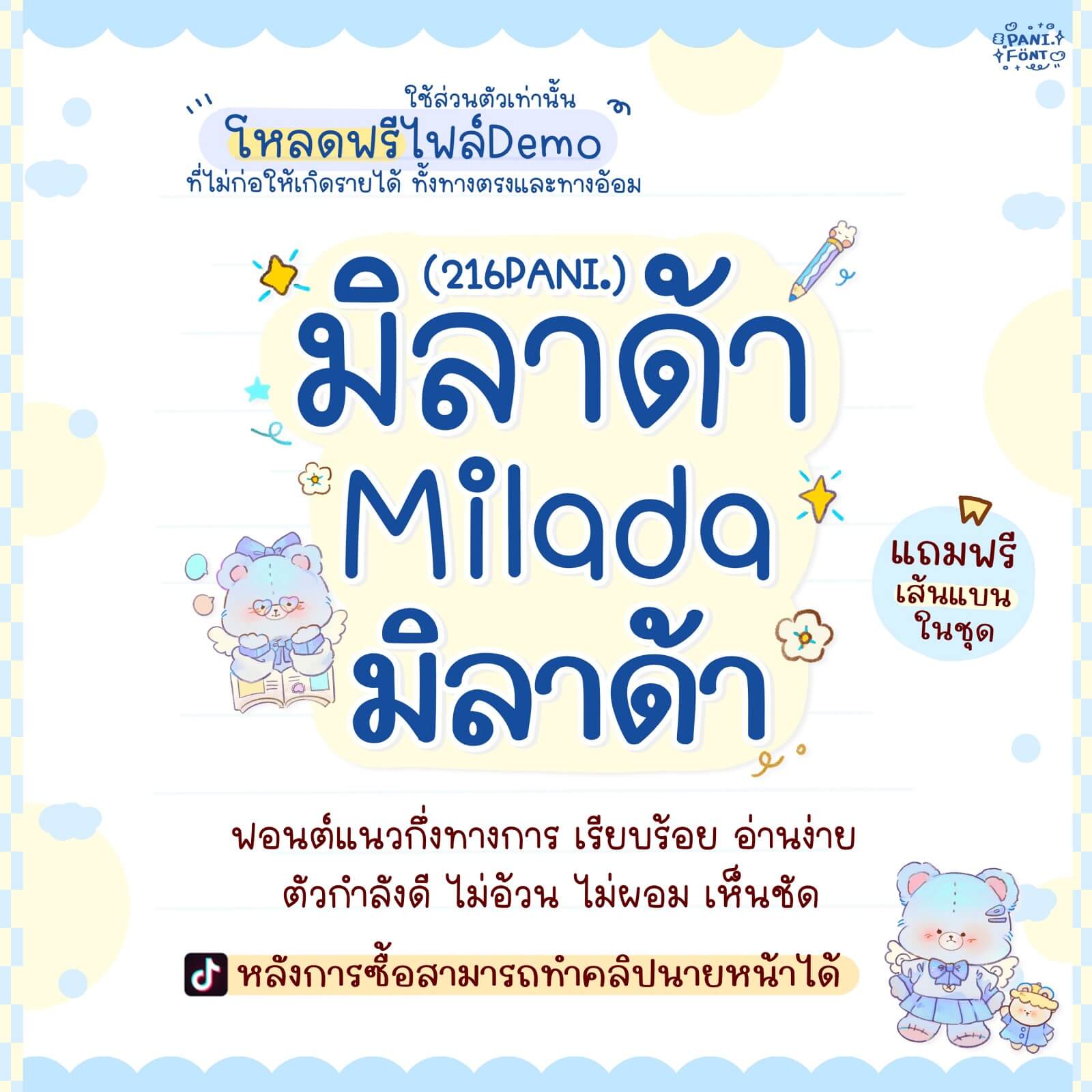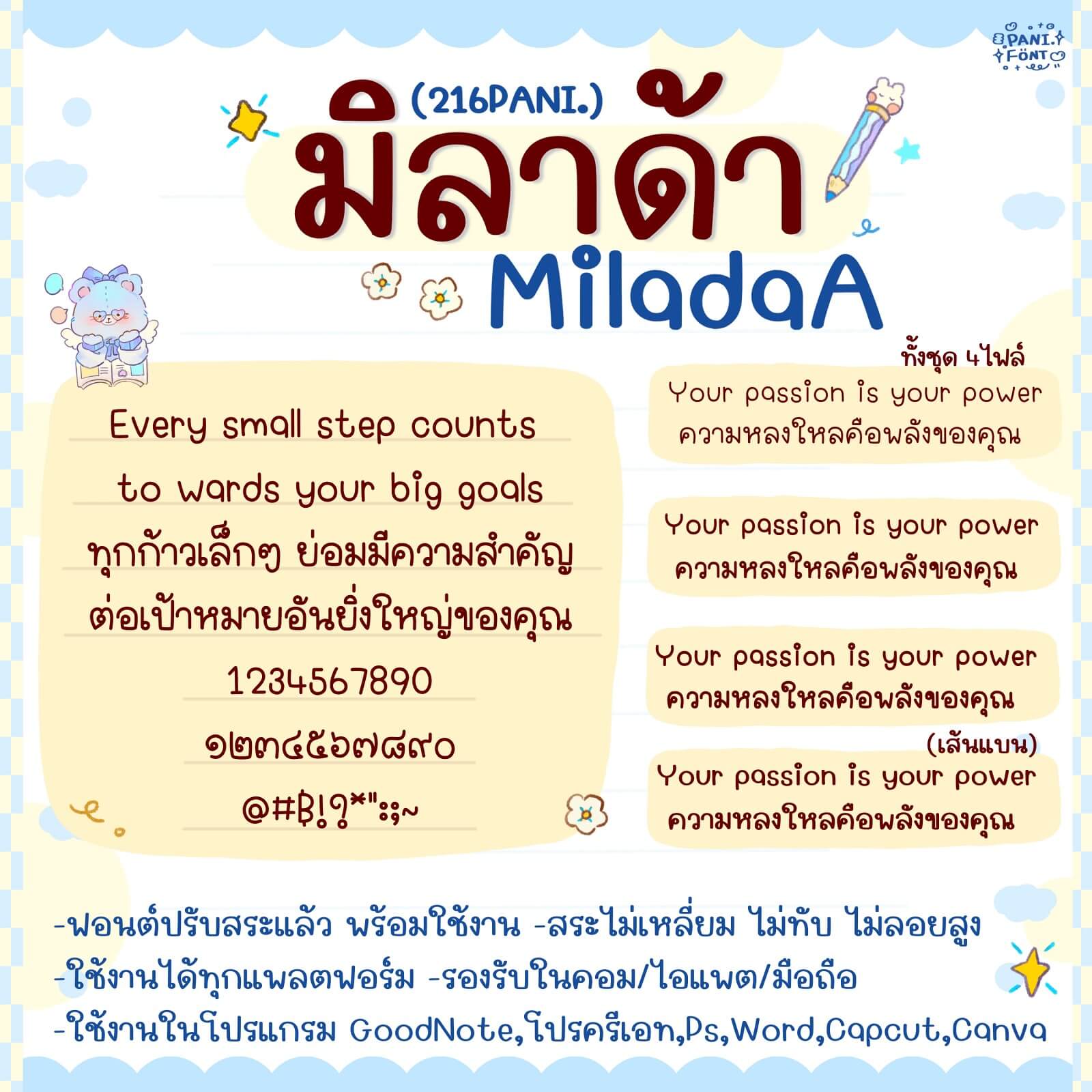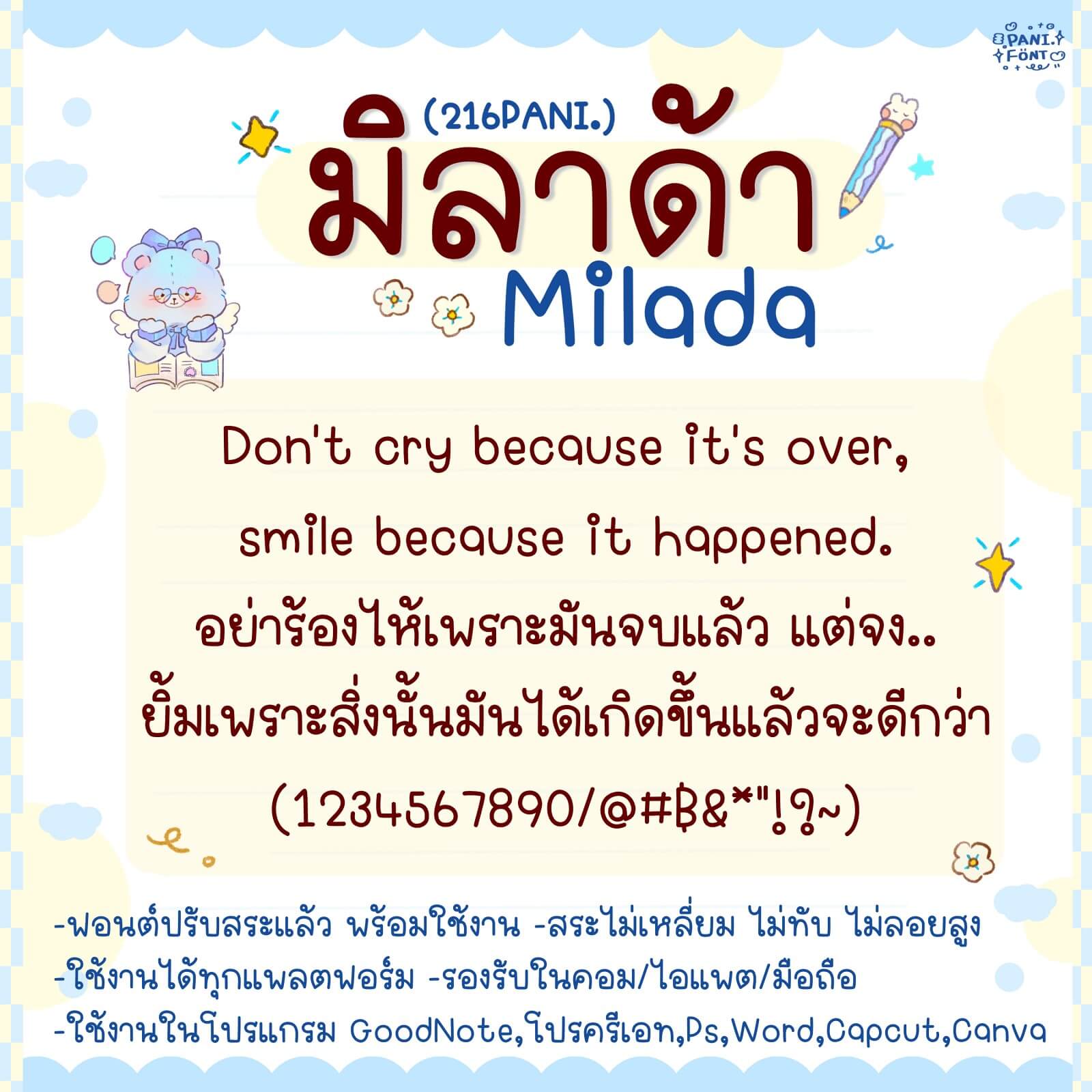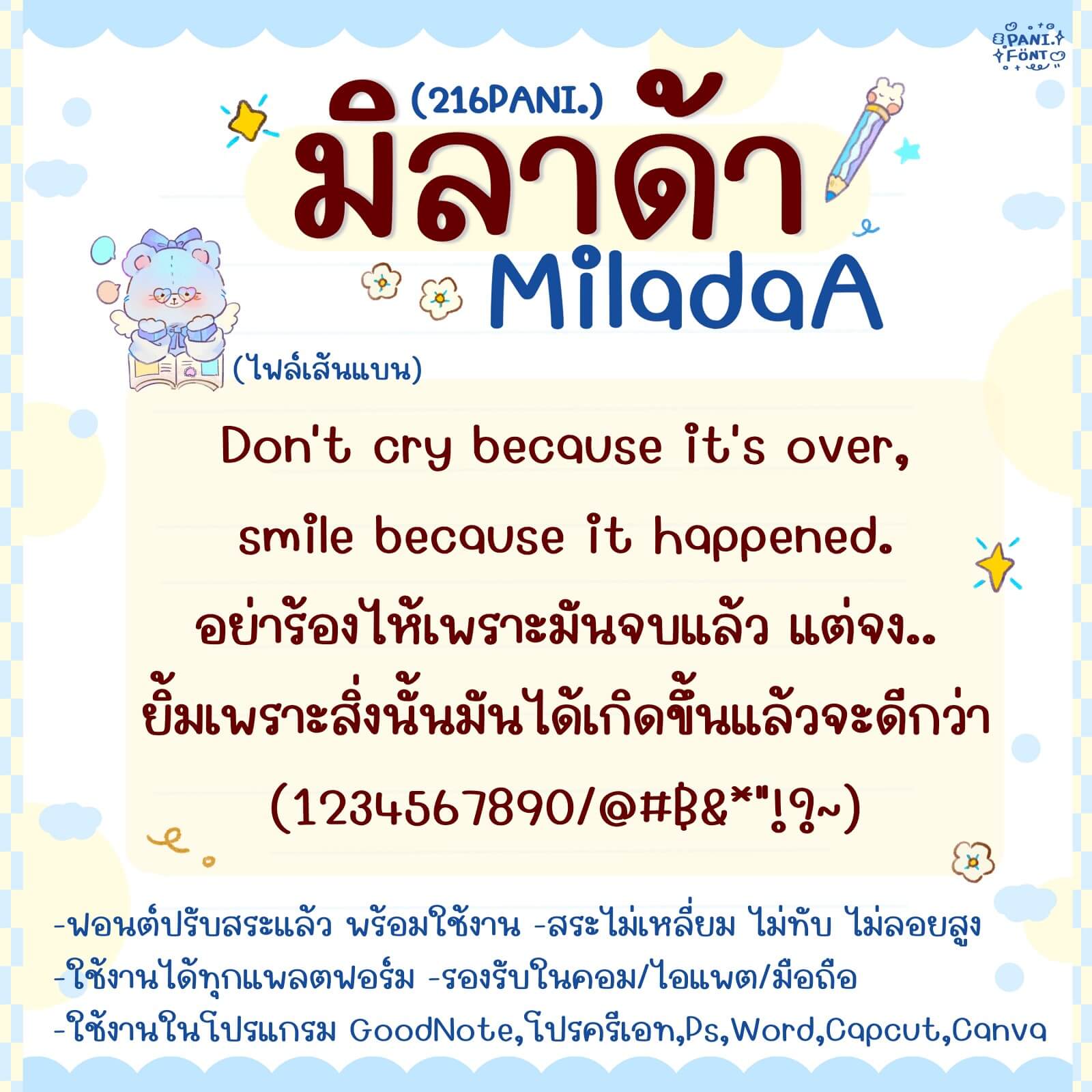
216PANI.มิลาด้า
ฟอนต์ 216PANI.มิลาด้า+แถมของตกแต่ง – ฟอนต์แนวกึ่งทางการ เรียบร้อย อ่านง่าย ขนาดตัวกำลังดี ไม่อ้วน ไม่ผอม เห็นชัด
ฟอนต์มี 4 ไฟล์ – น้ำหนัก บาง ปกติ หนา เส้นแบน